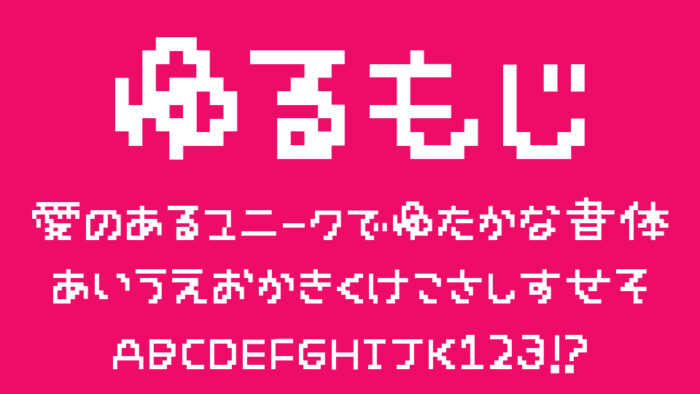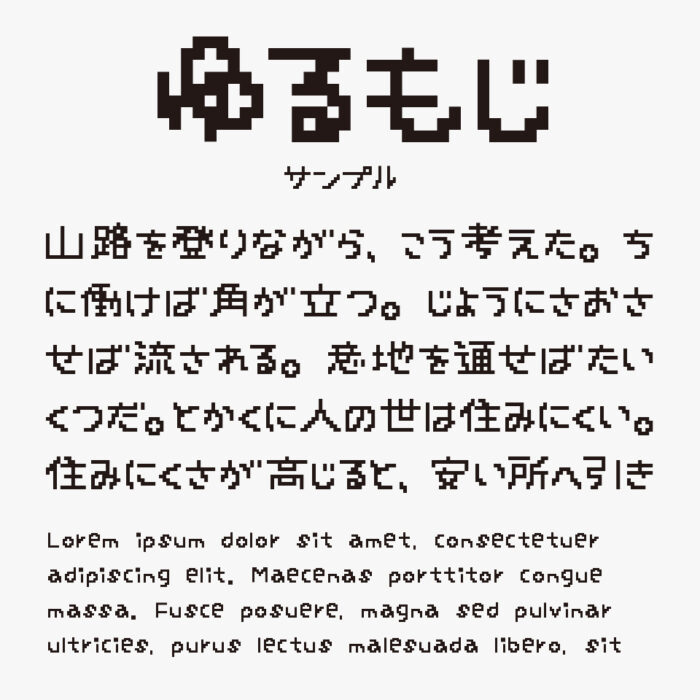
ゆるもじ
ゆるもじフォントは、ドット絵のような角ばったデザインながら、ふんわりした親しみやすさを感じさせるユニークなドットフォントです。
ドットで構成された文字にも関わらず、読みづらさはなく、丸みがあるやわらかな印象を生んでいるのがデザインが特徴です。ゆるさとドットレトロ感のバランスが絶妙で、個性的な見出しや遊び心のある表現にぴったりなフォントです。
ゲームやサムネイル、テロップなどの場面にもぴったりです。
収録文字は、漢字(小学1年〜4年)・ひらがな・カタカナ・アルファベット・数字・記号が収録されています。